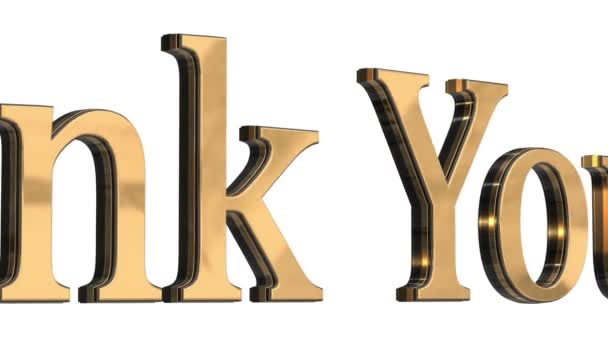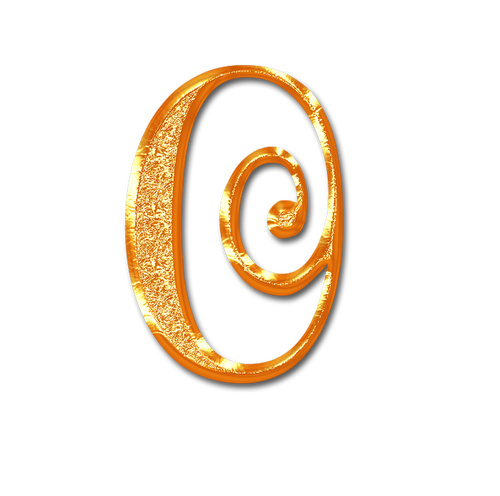
Надпись онлайн золотыми буквами: Написать золотыми буквами онлайн — Шрифт Marck Script — Конструктор html5 надписей — Скачать шрифты — Онлайн генератор текста создать сво…
огненный, 3D, анимированный, объемный, текстурный и пр.
Мне нужно написать красивый текст, желательно 3D-шрифтом, но я не владею графическими редакторами (Фотошоп, Gimp и пр.). Пробовал разобраться с инструкциями, но не получилось. Не подскажите, можно ли как-то еще просто и быстро написать красивый текст (без специальных знаний)?
Конечно, в графических редакторах можно нарисовать всё что угодно, правда без «набитой» руки придется повозиться… 👌
Но сейчас уже довольно много специальных сайтов, где можно быстро и легко написать любой текст (кстати, так часто создают различные логотипы), например, такие популярные, как 3-D, огненный, анимированный и прочие.
Всё, что потребуется от вас — это выбрать нужный шаблон (заготовку), написать свой текст, указать размер шрифта, и, собственно, получить на выходе готовую продукцию..
И так, приведу самые лучшие сайты (на мой скромный взгляд).
Лучшие сайты для создания красивых надписей и логотипов
На сайте доступны десятки и сотни самых разнообразных шрифтов (часть из них представлена на скриншоте ниже).
Выбрав нужный шрифт (шаблон) — и настроив размер, тень, обводку и пр. параметры, можно за считанные минуты создать свою красивую надпись.
Подборка шрифтов (шаблонов)
Обратите внимание, что после выбора шрифта, для более точного отображения вашей надписи, пройдитесь по всем вкладкам: лого, тень, фон, образ. В каждой из них вы можете настраивать различные параметры, которые в режиме онлайн будут изменяться на превью.
Еще один очень хороший сайт для написания самых различных текстов: анимированных, огненных, неоновых и пр.
Особо хочу отметить просто огромный выбор шрифтов: их несколько сотен. Причем, ведь главное количество — а качество! 👌 С этим у сайта все в порядке, каждый шрифт детально проработан и смотрится просто на загляденье!
Варианты шрифтов
Несмотря на то, что сайт не поддерживает русского языка — пользоваться им просто и легко. После выбора шрифта, напишите сам текст и укажите его размер. Изменения будут показаны в режиме онлайн (т.е. то, что видите — то и редактируете).
Редактирование огненного текста
Еще один очень интересный сайт с сотнями разнообразных шрифтов: золотые, неоновые, анимированные, объемные и т.
д. Сайт также англоязычный, но все действия просты и ясны (ничего сложного и запутанного).
Примечание: перед тем, как выбрать вариант шрифта — напишите в верхней строчке свой текст.
Примеры шрифтов
Кстати, отличительная черта ресурса от остальных: возможность создать очень высококачественную надпись (лого), задать необычный фон. В общем-то, выглядит это очень красиво и необычно!
Пример 3-D текста
На это сайте кривых шрифтов, подобно предыдущим, нет, зато есть очень красивые значки (стикеры), которые можно использовать при написании различного текста в чатах, мессенджерах, и пр.
Значков на сайте огромное количество и на самые разные темы, часть из них можете увидеть на скриншоте ниже.
Значки
Пример, как выглядят подобные значки в тексте показан ниже: подобный текст можно скопировать (Ctrl+C) и вставить куда-нибудь (Ctrl+V) — ваш текст вставиться вместе с этими значками.
Интересно и оригинально!
Сообщение для чата со значками
Русскоязычный сервис с десятками разнообразных шрифтов. Хочу особо отметить, что на сайте собрано множество шрифтов с анимацией.
После выбора шрифта, можно задать цвет текста, ширину, высоту, фон, наличие анимации, эффекты и пр. настройки.
👉 Кстати, поддерживает написание текста на русском языке! (некоторые сервисы выше вместо русского текста показывают крякозабры).
Примеры шрифтов
Отличный сервис для онлайн-генерации разнообразных надписей красивым шрифтом. Поддерживаются десятки самых разнообразных шрифтов, которые все разбиты на несколько разделов: печатные, плавные каллиграфические, техно, готика, декоративные сказочные, контурные и др.
Примеры надписей
Пример полученного текста
(Добавление надписей на картинки и фото)